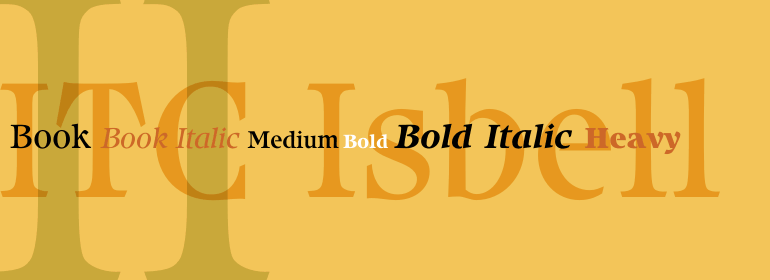
ITC Isbell®
ITC Isbell®,这款字体结构工整、笔画清晰,兼顾美观与易读性,适用于标题、正文、海报、包装、LOGO 等多种场景。字形优雅稳定,风格百搭耐看,适配日常排版与创意设计,让文字呈现更舒适、更具质感。ITC Isbell®一笔一画,皆是细节,以均衡的比例、流畅的线条打造舒适视觉体验,字形端正大气,风格简约现代。无论是商业设计、品牌宣传还是日常排版,都能轻松驾驭,让文字更有格调与力量。ITC Isbell®字体下载。
ITC Isbell字体是密歇根州底特律的Dick Isbell和Jerry Campbell的作品,这是一种高度风格化的罗马字体,有着非凡的易读性。同寻常的弧线以及几个小写字符的曲线赋予了字体个性。ITC Isbell字体适用于广告、小册子、菜单以及各种其他应用程序。
ITC Isbell font is the work of Dick Isbell and Jerry Campbell of Detroit, Michigan, a highly stylized roman typeface which retains an exceptional legibility. The unusual arches and curves of several lowercase characters give the typeface its individuality. ITC Isbell font is ideal for advertising, brochures, menus, and a variety of other applications.